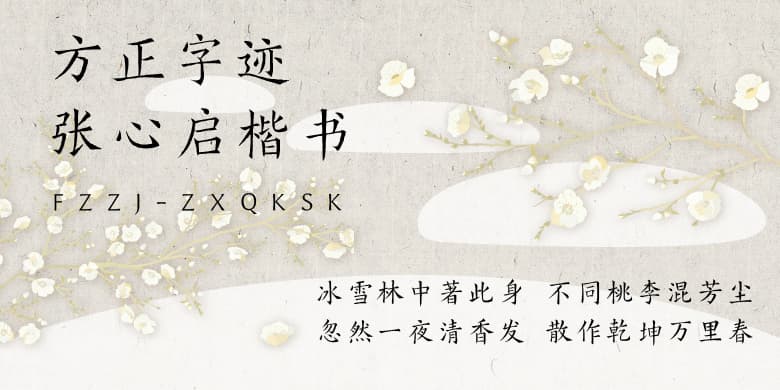
方正字迹-张心启楷书
方正字迹-张心启楷书点画以轻笔入纸,露锋作收。横画以逆入平出,有往必收。竖画取内直外曲之势,曲中见直。钩画以蹲锋蓄势,提笔出锋。提画入笔上仰,发力收锋。撇画起笔直划,出锋稍肥,力送到位。短撇落笔左出,快而峻利。捺画逆锋轻折锋铺毫,收锋如刀状。字体结构匀称合理,古朴端正,骨气劲峭,法度严谨,笔画舒展有力,收放自如,结体遒劲,流畅自然,凝重大方。适用于报纸、杂志、书籍印刷等。